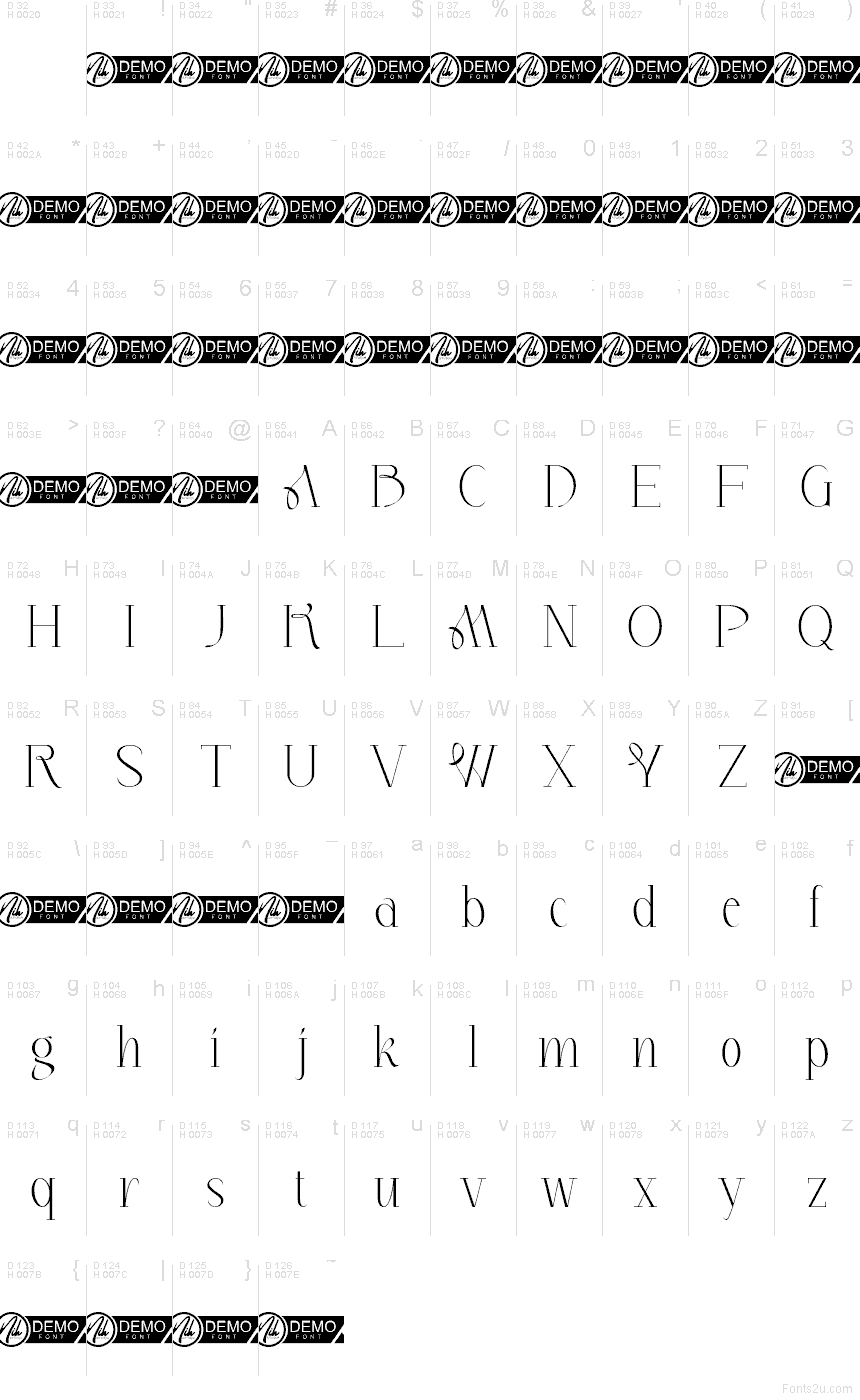
Amanda Roies Demo
Amanda Roies من NihStudio هو خط عرض مجاني بنمط ريترو، يتميز بحروف طويلة ذات تباين عالٍ ومنحنيات هوائية انسيابية تضفي على التصميم لمسة راقية تشبه ملصقات السبعينيات. ينبع إيقاع هذا الخط من الخطوط العمودية النحيفة والأشكال المستديرة الناعمة والزخارف الانسيابية التي تحول النص إلى عنصر ديكوري بامتياز.
هذا المزيج يجعل من Amanda Roies خياراً طبيعياً لشعارات المتاجر الفاخرة، والتغليف، وعناوين الموضة، وأغلفة الألبومات، وهويات المطاعم التجارية. تمنح الامتدادات الأنيقة والتباين الجذاب للكلمات القصيرة طابعاً درامياً مناسباً للدعوات أو تصاميم وسائل التواصل الاجتماعي، خاصة عندما تبحث عن لمسة من سحر الماضي (فينتج) لتتميز عن الخطوط العادية.